在平面设计中,字体的设计往往会给平面增色不少,但是要设计好字体,还是需要掌握一些和字体相关的内容。那么大家都来了解一下设计的字体吧。
在进行设计时,文字主要是有两个功能,作为信息传达的载体,或者是起到一定的美化作用。注意在设计的时候要避免失去识别性,这是它最重要的作用。
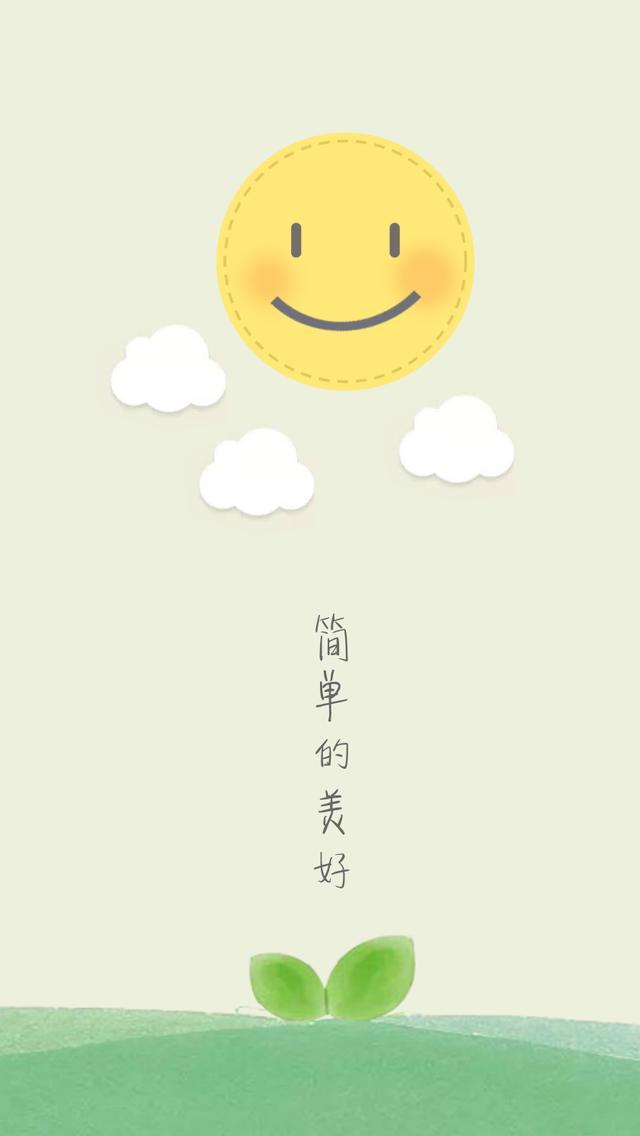
在设计平面的时候,大家使用最多的就是汉字以及英文,其实这二者有着很大的不同,英文字体一般比较有高端感,时尚感,而中文则是比较浓郁,有韵味的。
在英文下有着很多的分类,常见的为衬线体,无衬线体,此外还有一些字体都比较有个性,例如哥特体庄严高贵,具有紧张感,手写体则比较优雅,亲切。
汉字的字体则是更加丰富,常使用的便有宋体,黑体,以及其它的一些字体,基本上每种字体的表现和个性都不同,大家可以在设计中灵活使用。
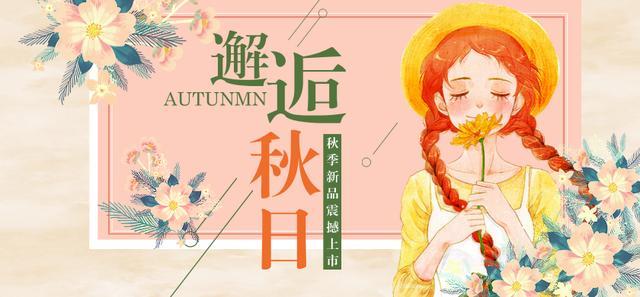
不同的字体给人的感觉是不一样的,基本上大家在设计中带有比较常见的风格。
高级感的字体一般是衬线体,尤其是文字上有装饰,搭配留白,会显得更加华丽大气,具有高级感。
亲和感强的字体多是一些比较圆润的,柔美的,但是不要过于浑圆,这样才能展示亲和,而不会显得孩子气。
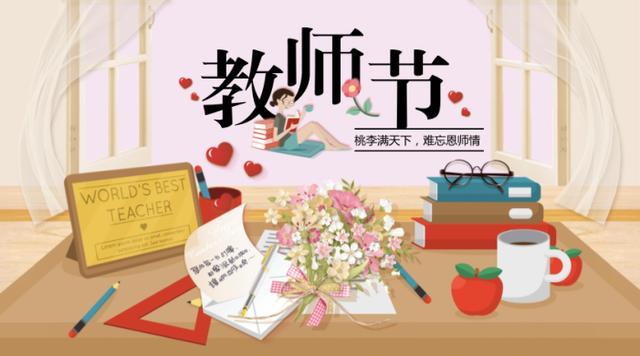
华丽的字体多是具有装饰元素,装饰性越强,字体越华丽,但是这可能会降低文字的可读性,因此在使用的时候要注意。
复古感的字体则主要是选择一些旧时代流行的字体,来展现复古的感觉。而比较有韵味的字体,多是书法字体。手写字体则是比较灵活,有趣,显得比较自然的字体。
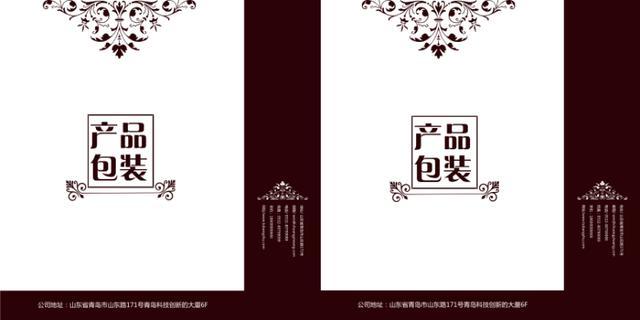
其实在设计字体的时候,本质上还是为主题服务,大家主要还是小心使用,力求使文字符合大家的需求。